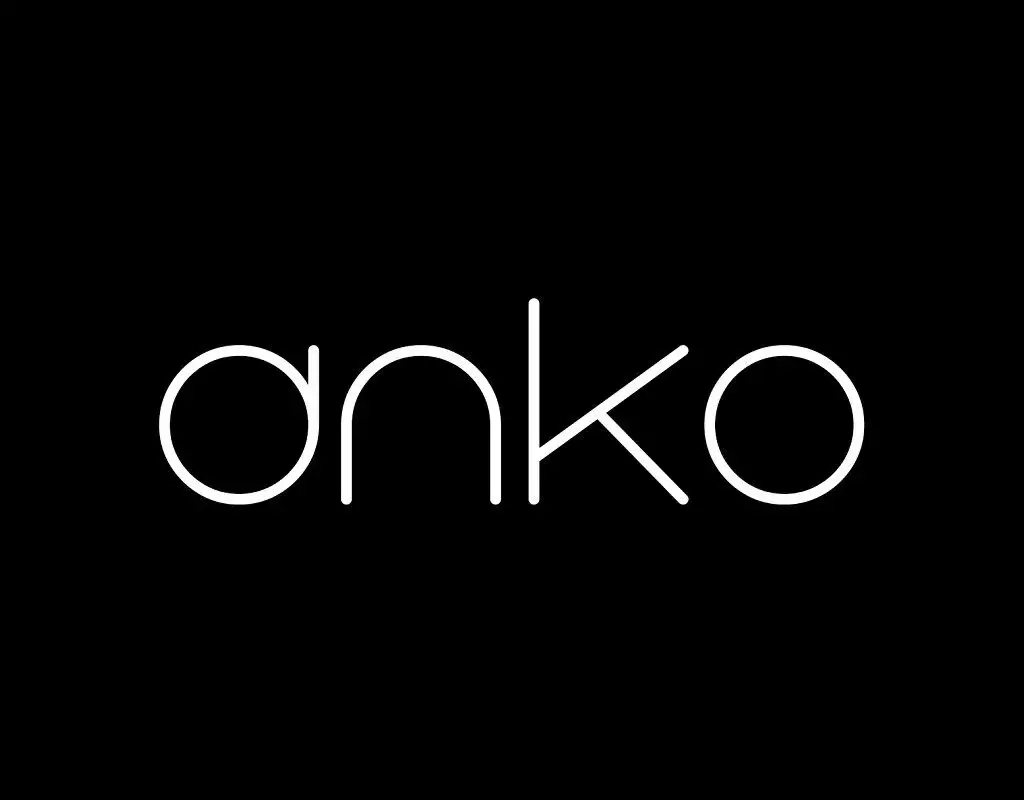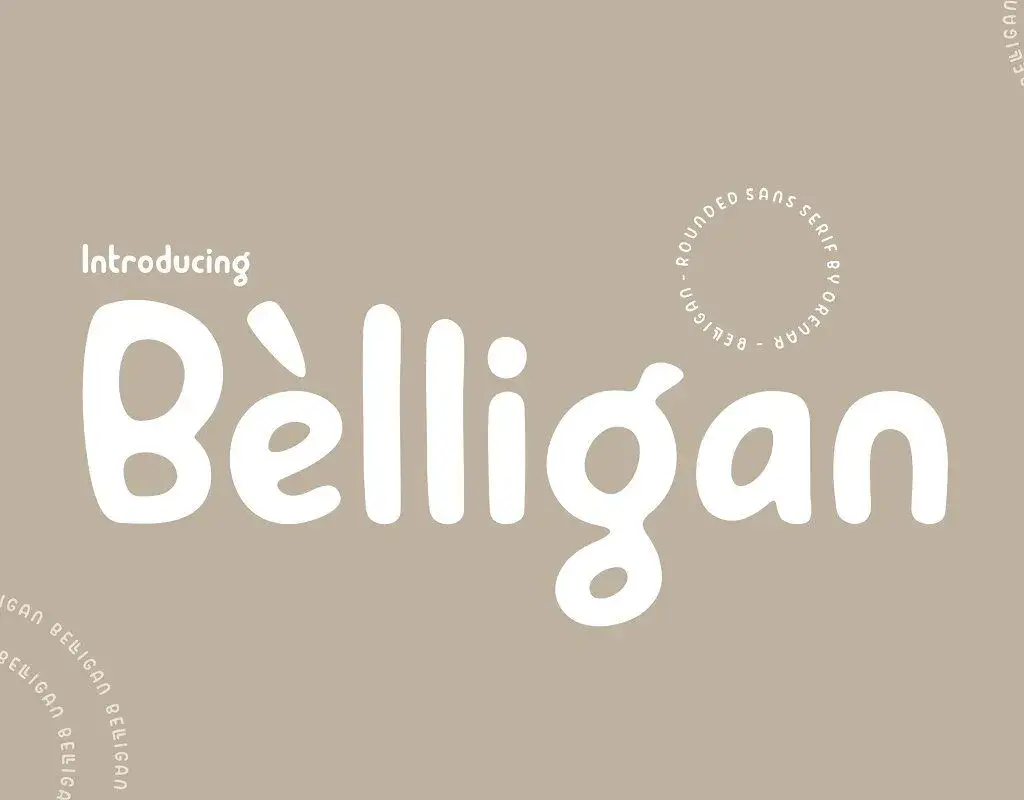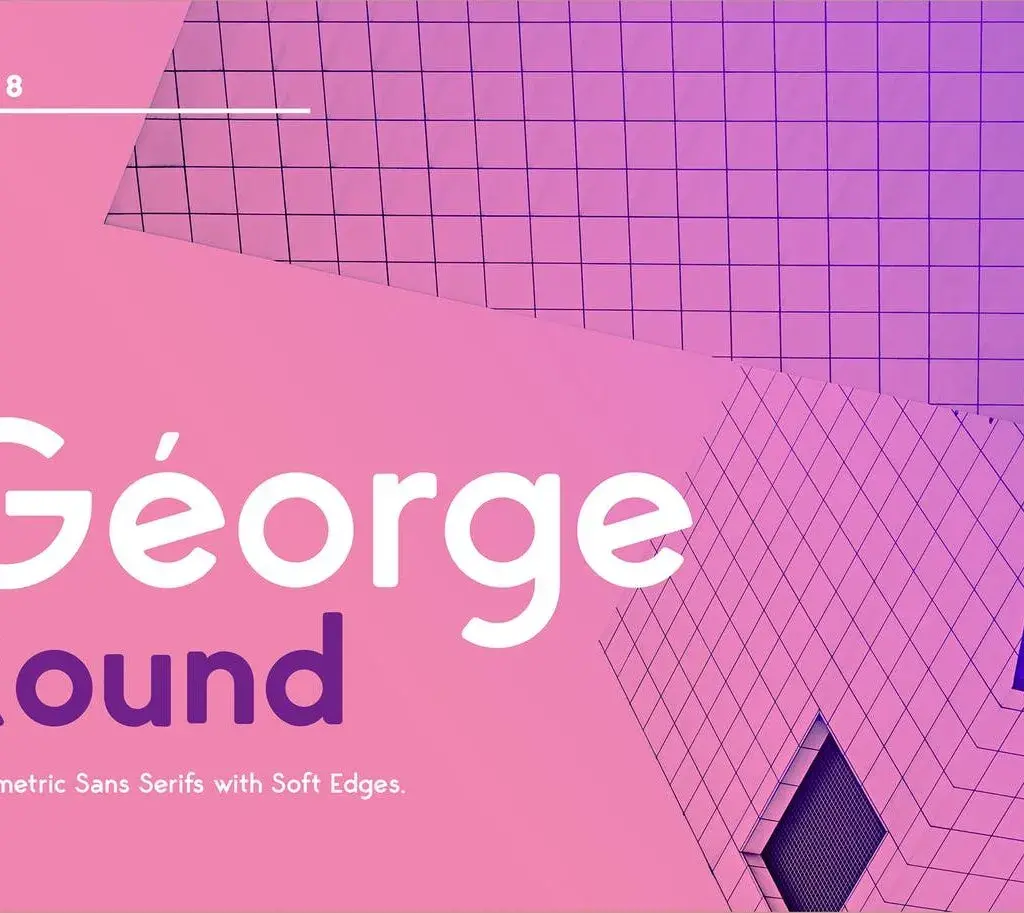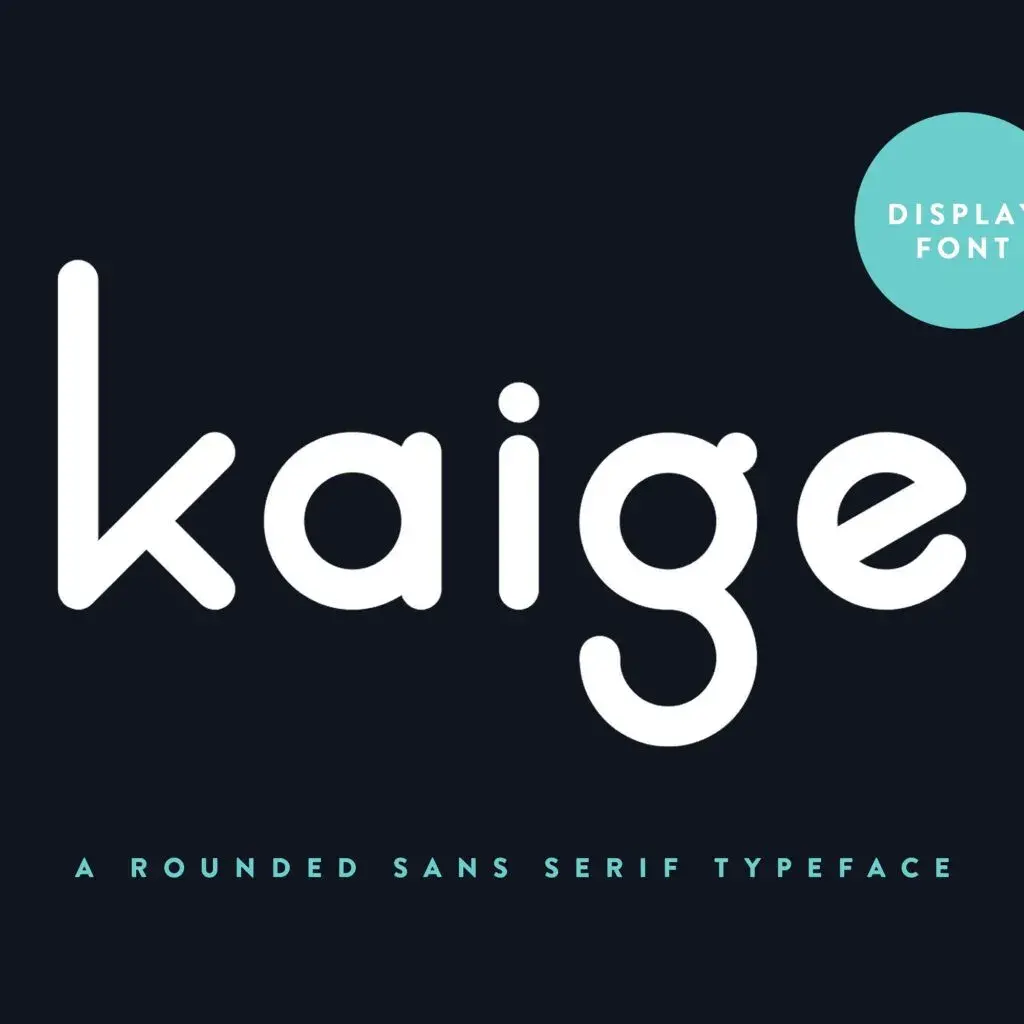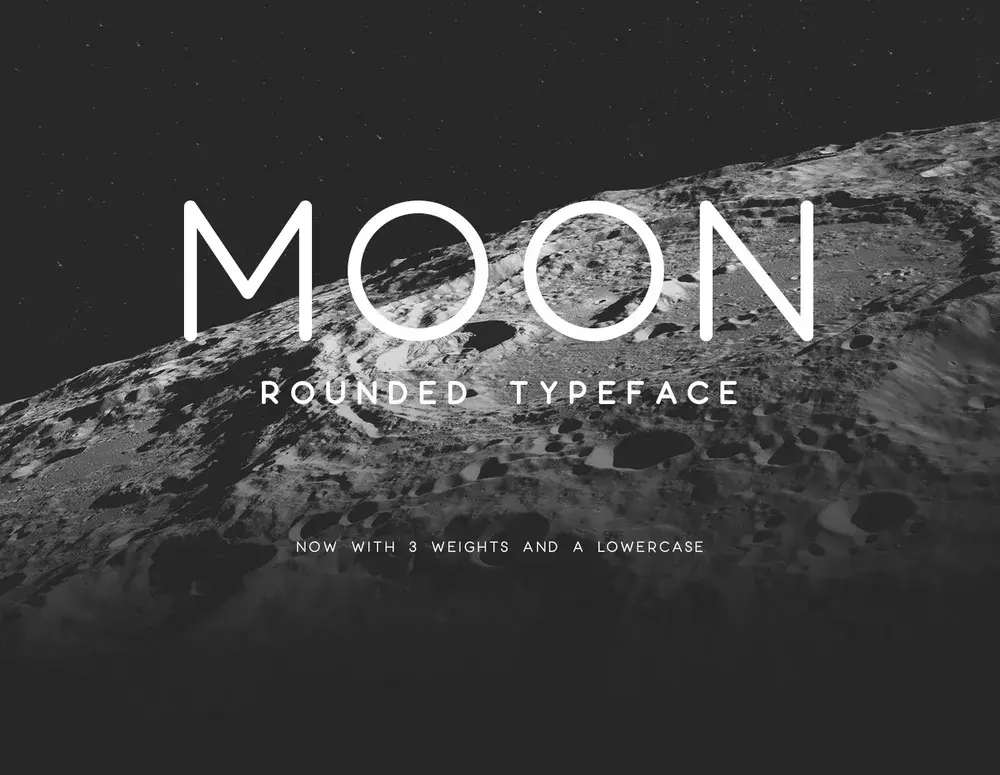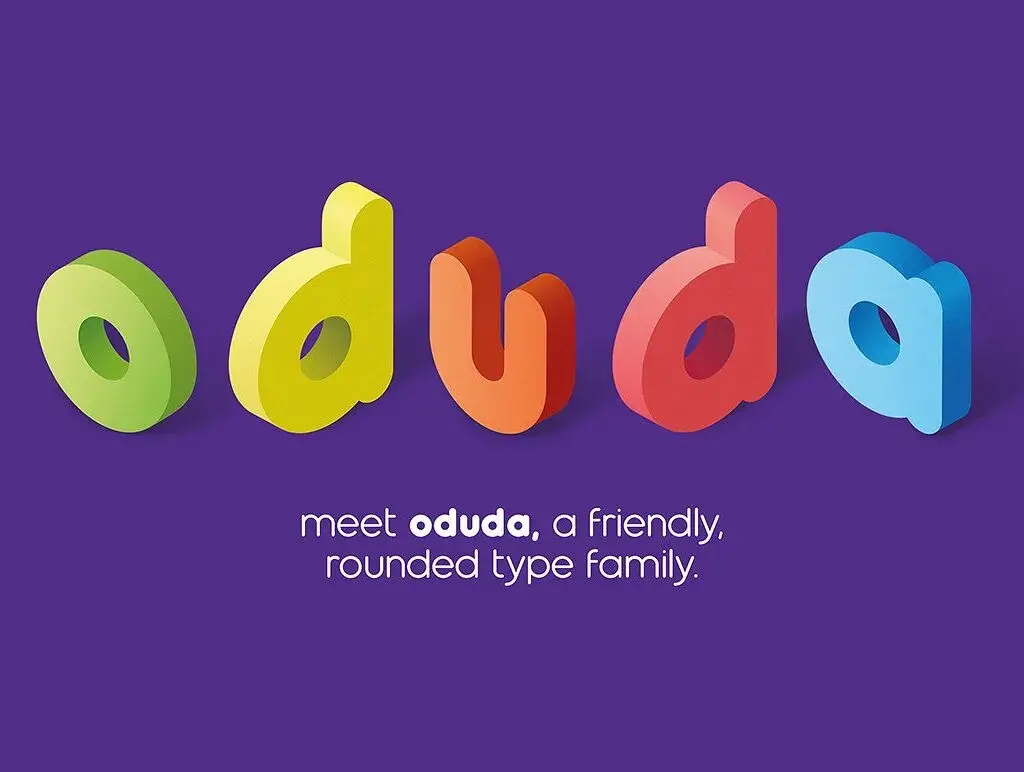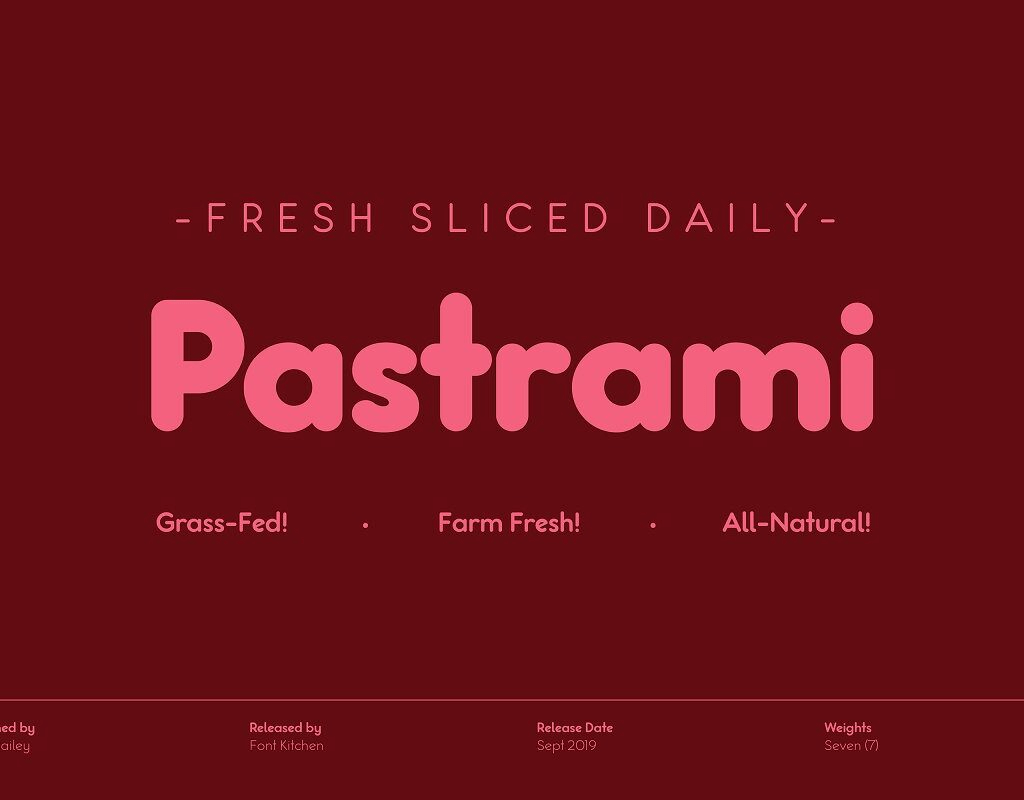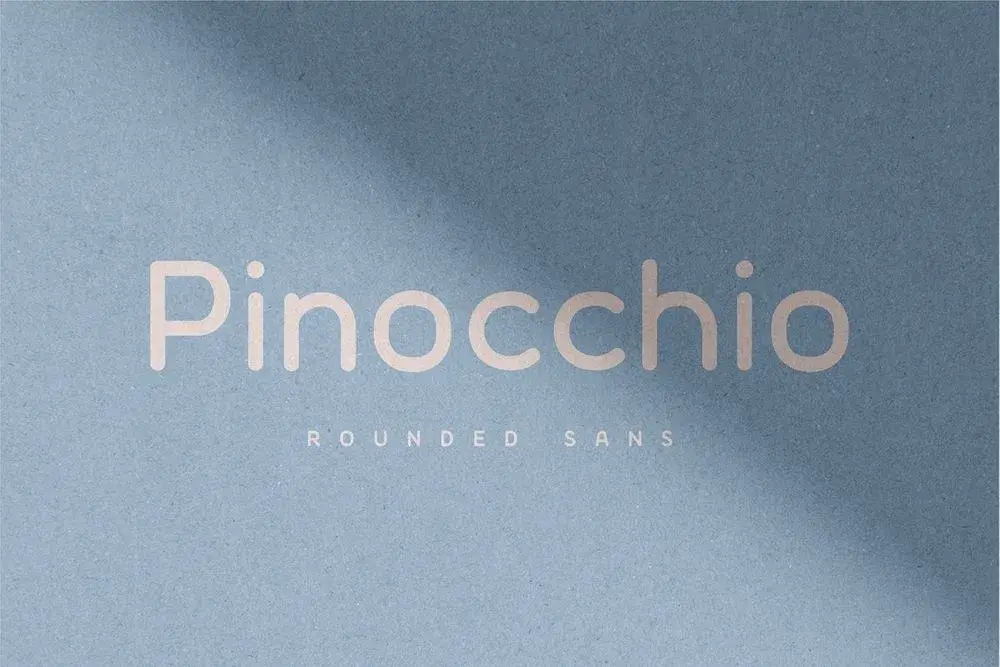
10 typographies arrondies pour vos projets graphiques
Les polices d’écriture arrondies sont très appréciées par les designers en tous genres. Et pour cause, elles possèdent un aspect à la fois sérieux, décontracté, ludique et élégant : idéal pour apporter une touche de nouveauté et d’originalité à n’importe quel projet. Dans cet article, nous vous proposons de découvrir 10 typographies arrondies gratuites et premium, parfaites pour la création graphique et la conception de site web.
Reef
Une police d’écriture arrondie simple, sobre et efficace.
Belligan
Une police arrondie sans serif à la fois calme, féminine et élégante.
Pastrami
Une typographie arrondie inspirée des polices de caractère chaleureuses et fantaisistes des restaurants américains des années 70.
Pinocchio
Une police de caractère arrondie sans empattement, avec un look épuré et enfantin.
Anko
Une typographie arrondie minimaliste, idéale pour les projets liés au monde de la mode.
Moon
Une police d’écriture arrondie et élégante, gratuite pour un usage personnel.
George Round
Une police arrondie sans empattement, conçue avec une géométrie moderne et stylisée.
Oduda
Une typographie agréable et ludique grâce à ses élégantes formes rondes.
Yikes
Une police de caractère arrondie idéale pour les logos, les titres et les affiches.
KAIGE
Une police d’écriture arrondie aux lignes épurées et aux formes douces.